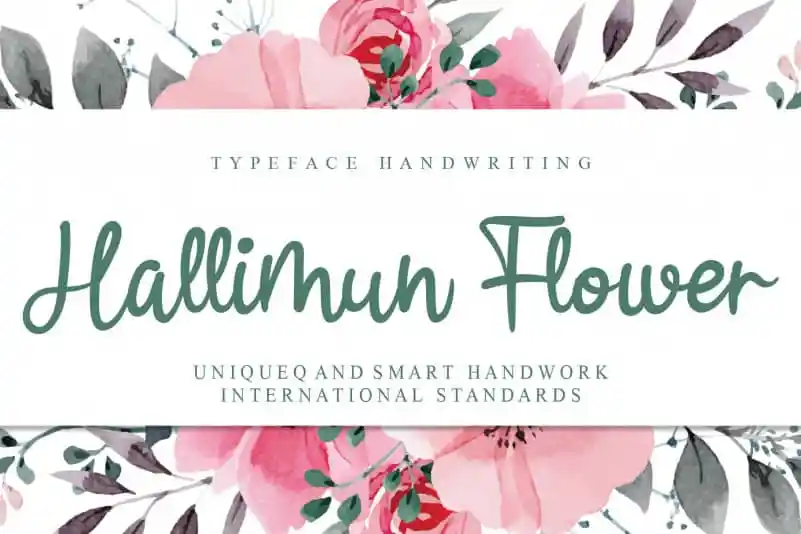
Hallimun Flower Script Font – Fonte Grátis
Hallimun Flower Script Font
A Hallimun Flower Script Font é uma elegante e delicada fonte escrita a mão que apresentará seu estilo único no mundo digital. Suas letras distintas e bem redondas fomentam um verdadeiro trabalho de arte. Este tipo de fonte possui um poder incrivelmente versátil, perfeito para os designers apaixonados por transformar ideias em realidade. Adentre o encanto deste texto, faça suas criações brilharem com este estilo único e seja atraído pelo poder criativo desta fonte. Englobe seus projetos digitais com a Hallimun Flower Script Font, um verdadeiro toque de sofisticação e originalidade.